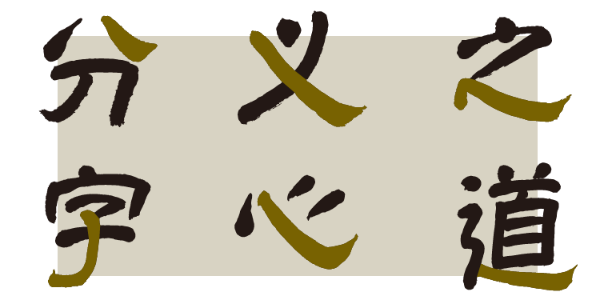
端整古秀,朴拙大方的一款古隶
书写字体
传统 / 书法 / 隶书 / 古朴
标志 / 书籍 / 杂志 / 展览 / 艺术
汉仪文博古隶缘起于2019年全国设计师书法展,由汉仪签约作者张文博书写。张文博的创作建立在传统书画整体观照之上,重视笔墨的格调。这款书法字体取法古隶,朴拙大方,庄重而内敛,既具备传统书法的精神气质,又满足字库传播和使用的实用功能。这款字体适合作为标题字体应用于文化艺术领域,传达直接而朴素的力量与美。
古隶,汉隶形成之前的隶书,较多古汉字笔意,是尚未成熟的早期隶书。隶书形成于战国晚期,秦国文字相比于战国时代其他国家的文字较为保守,在日常使用文字的时候,为了书写的方便,而不断破坏、改造正体字形,文字笔画趋向省减和平直,由此产生的秦国文字的俗体就是隶书形成的基础。
甲骨文、金文、篆文大多彰显刻工刀法,而自秦简开始,书于竹帛的古隶保留了书写线条,人们得以直接欣赏毛笔墨迹。
在具体书写时,作者有意将传统隶书左右舒张的取势变为正方形,使整个字看起来既敦厚又不失灵动。将传统隶书中秀美与朴拙一路的风格与摩崖石刻的线质融合起来,使每个字看起来既庄重又内敛。
由篆入隶,乃书法史上的大事,隶书破圆为方,确立了方形的汉字“横平”“竖直”的基本构成。汉仪文博古隶的字形体势平整,中宫放松,而笔势略向右去。
另一方面,书写线条得以保留,书写者的情绪流露于笔锋。作者张文博强调汉字书写的笔法和传统,在汉仪文博古隶这款字体中:不难发现传统书法的笔法和特征在每一个字中克制地有所着重:
波磔,形容隶书水平线条之飞扬律动,尾端的笔势扬起而出锋。古隶少有后代隶书鲜明的笔法风格,这款字体取其骨架而加以巧饰,波磔笔较为内敛,收笔处轻轻挑笔,有微微上扬之势。
长掠温润敦实,弯掠、横掠拙中见巧,短掠反向上提。
捺笔起笔藏锋,捺出气势,有力而灵巧;弯钩、抛钩、走之旁坚实而自然。
点画俯仰有致,或圆而短促,又或与短掠一并上提,在温厚敦实的字形之中增添了一笔灵巧。
这款字体中包含大量异体字,在汉字字形漫长的演变过程中,尤其是早期隶书形成的过程中,新旧字形往往并存,纵惯汉字的发展,汉字的总数也是不断增多的,异体字也占其中的一部分。作者在书写创作中或取碑帖中的异体字,或取篆书古文字写法,或取书法艺术中常见的异态写法,赋予整套字库古韵。
汉仪文博古隶的西文部分由汉仪字库的西文设计师史贺达设计,为了让西文字体能够传达出古隶的高古朴茂,而选择以安色尔体(Uncial)为基础进行设计。安色尔体是一种在公元4—8世纪广泛流行于拉丁文化圈的誊抄字体 ,与当代罗马体在结构上有着较多差异,如此一来,西文语境下也能够体会到其中蕴含的历史感和神秘感。
书写体的笔画线条于古隶之波磔相呼应,秀美而古雅。
西文部分书写的差异化写法和中文部分的异体字极具历史文化底蕴。